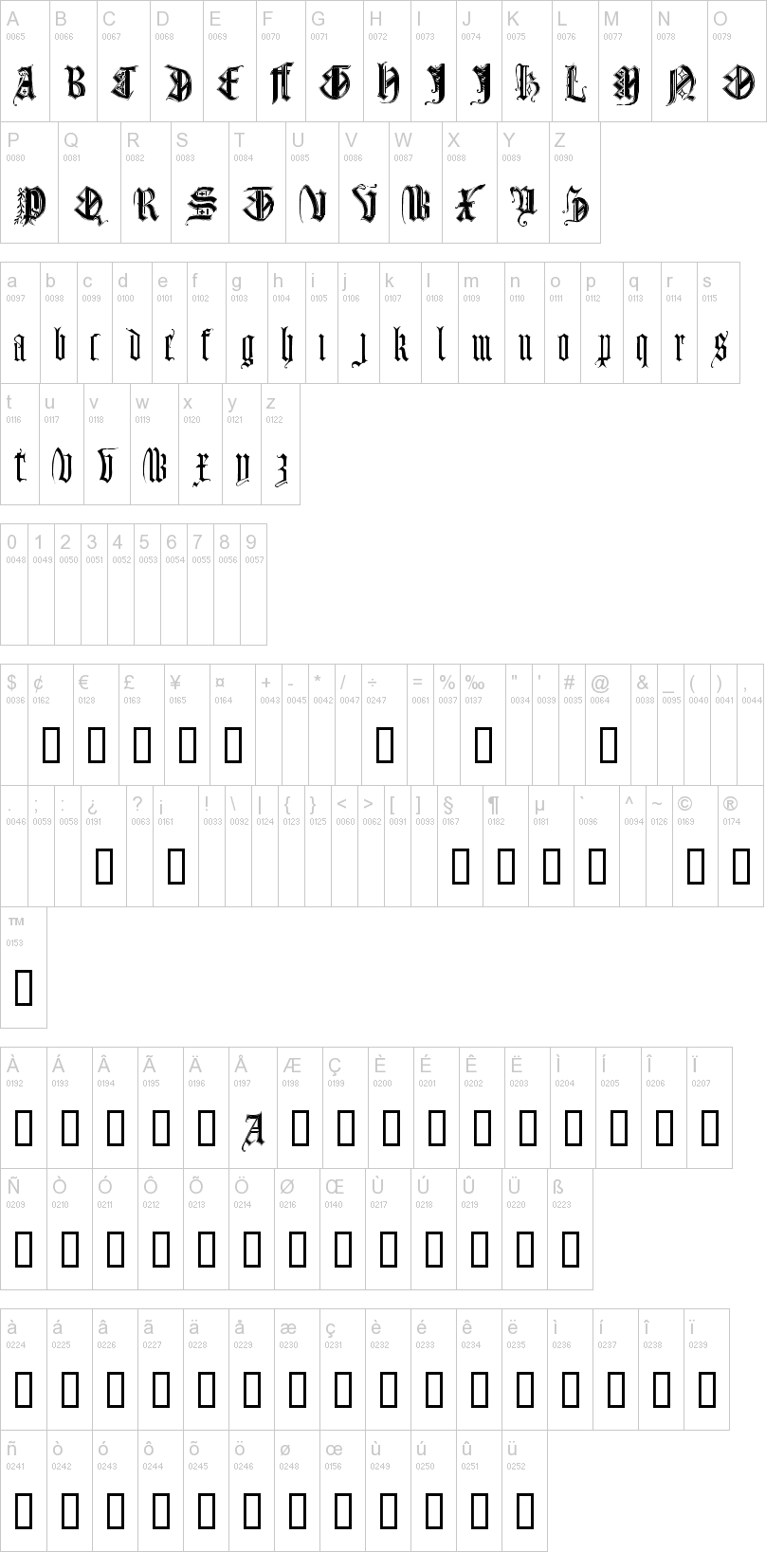
Monumental Gothic
Monumental Gothic字体是一种非常流行的英式哥特式字体,它的特点是它的字体设计具有柔和的曲线和饱满的粗体。它的字体特征是它的字母形状是一种混合形状,既有细线又有粗线,这使它看起来具有柔和的曲线,很容易让人联想到古老的建筑结构,因此得名为“建筑式”字体。它也具有英式哥特式字体的特点,如大小写字母的不同,以及单词之间的空格。它是一种通用字体,可以用于印刷、网页设计、排版等。
Monumental Gothic是一款非常不错的手写艺术字体,具有很好的视觉感,适合于文化类的宣传设计、商业类品牌的广告和产品包装设计以及个性化文字排版等较多场景。